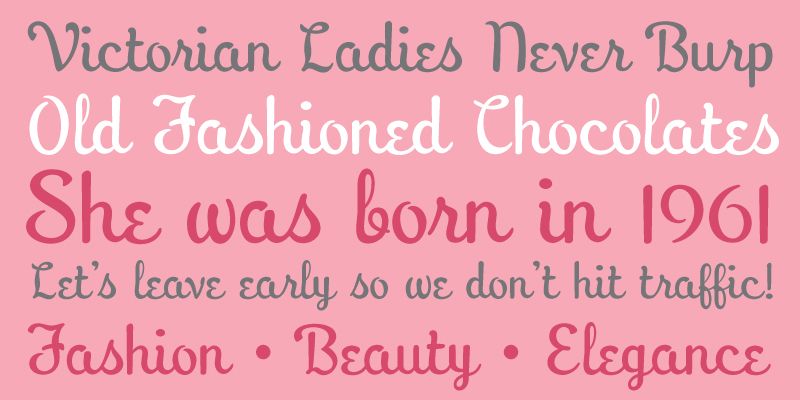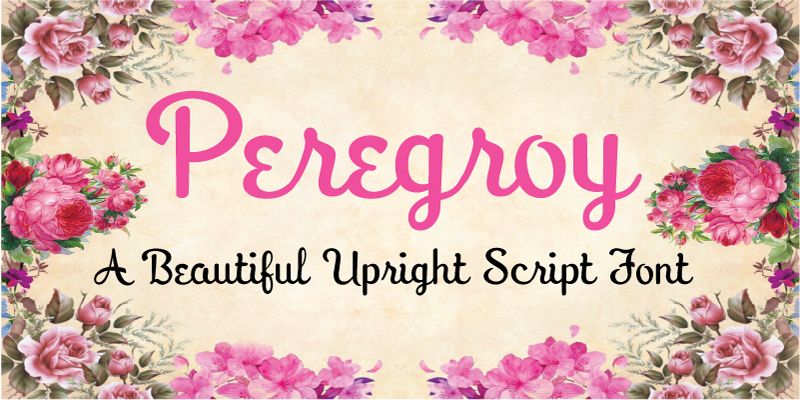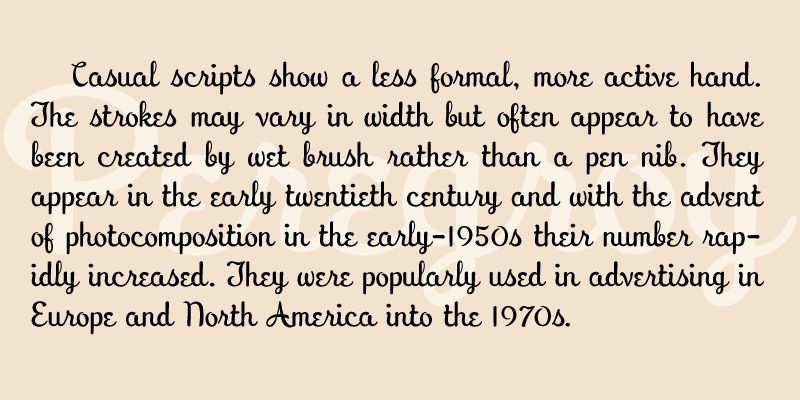
Inspiré par les titres écrits à la main d’un film d’animation populaire, Peregroy est convivial et attrayant. Son charme féminin et sa simplicité lui confèrent un sentiment de bienveillance et d’accessibilité.